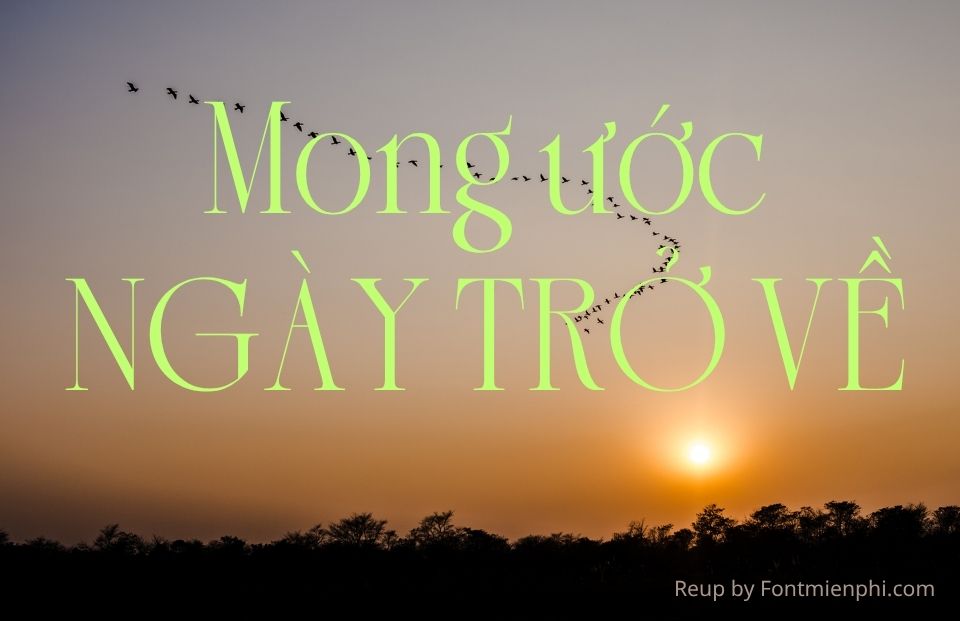
Tải Font Việt Hóa 1FTV VIP Makcasa  – Tinh Hoa Serif Hiện Đại
Nếu bạn đang tìm kiếm một phông chữ có chân (Serif) kết hợp hài hòa giữa nét cổ điển thư pháp và những đường lượn sóng hiện đại, thì Makcasa chắc chắn là mảnh ghép hoàn hảo không thể bỏ qua cho các dự án cao cấp.
🌟 Về Font 1FTV VIP Makcasa: Giao Thoa Giữa Cổ Điển & Hiện Đại
Nguyên bản của Makcasa là một Display Serif Typeface tuyệt đẹp được thiết kế bởi Timelesstype Studio. Với định hướng tạo ra sự sang trọng tuyệt đối, tác giả đã khéo léo lồng ghép những chi tiết sắc nét, tỉ mỉ cùng các đường nét lượn (swashes) vô cùng bay bổng.
Phiên bản 1FTV VIP Makcasa mang đến một cấu trúc serif vững chãi nhưng không hề thô cứng. Ngược lại, sự tương phản mạnh mẽ giữa các nét thanh và nét đậm tạo ra một cảm giác tinh tế, nghệ thuật và mang đậm phong cách thời trang thượng lưu.
💎 Đặc Điểm Nổi Bật Của Bản Việt Hóa Makcasa
• Việt hóa 100% chuẩn mực: Hệ thống dấu câu và ký tự tiếng Việt được tinh chỉnh kỹ lưỡng, đảm bảo văn bản hiển thị mượt mà, hài hòa với tổng thể mà không lo gãy nét.
• Ký tự thay thế phong phú (OpenType Features): Font hỗ trợ mạnh mẽ các tính năng như Ligatures (chữ ghép đep mắt), Stylistic Alternates và Swashes. Bạn có thể thoải mái biến tấu từng con chữ để tạo ra những tiêu đề (typography) độc nhất vô nhị.
• Cấu trúc Display hoàn hảo: Được thiết kế chuyên dụng để hiển thị ở kích thước lớn, các đường nét tinh xảo của Makcasa sẽ được phô diễn trọn vẹn, tạo sức hút thị giác cực mạnh.
🎨 Ứng Dụng Thực Tế Trong Thiết Kế
Với vẻ đẹp sang trọng và đẳng cấp, Font 1FTV VIP Makcasa là sự lựa chọn hàng đầu cho các dự án yêu cầu tính thẩm mỹ, nghệ thuật cao:
• Nhận diện thương hiệu (Branding & Logo): Đặc biệt lý tưởng cho các logo thương hiệu mỹ phẩm cao cấp, spa, trang sức, nhà hàng sang trọng hoặc các hãng thời trang.
• Thiết kế ấn phẩm cưới: Mang lại sự lãng mạn, cổ điển và trang trọng cho thiệp cưới, menu tiệc, hay thiệp mời sự kiện VIP.
• Biên tập & Xuất bản (Editorial): Làm tiêu đề nổi bật (headline) cho các tạp chí thời trang, lookbook nghệ thuật hay bìa sách.
• Truyền thông quảng cáo: Tạo điểm nhấn ấn tượng cho bao bì sản phẩm (packaging), banner website và poster sự kiện.